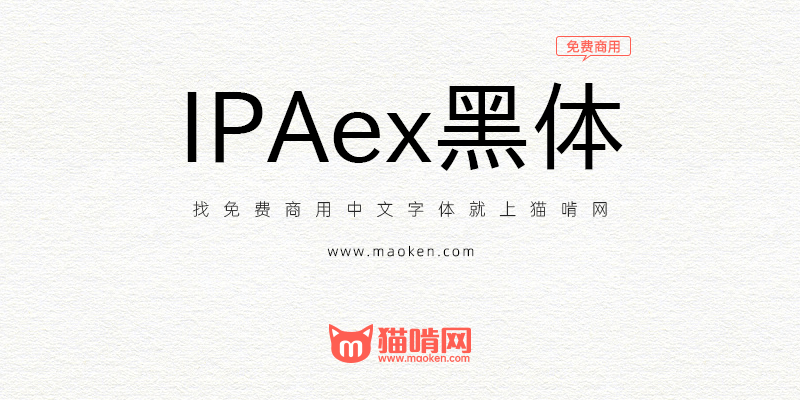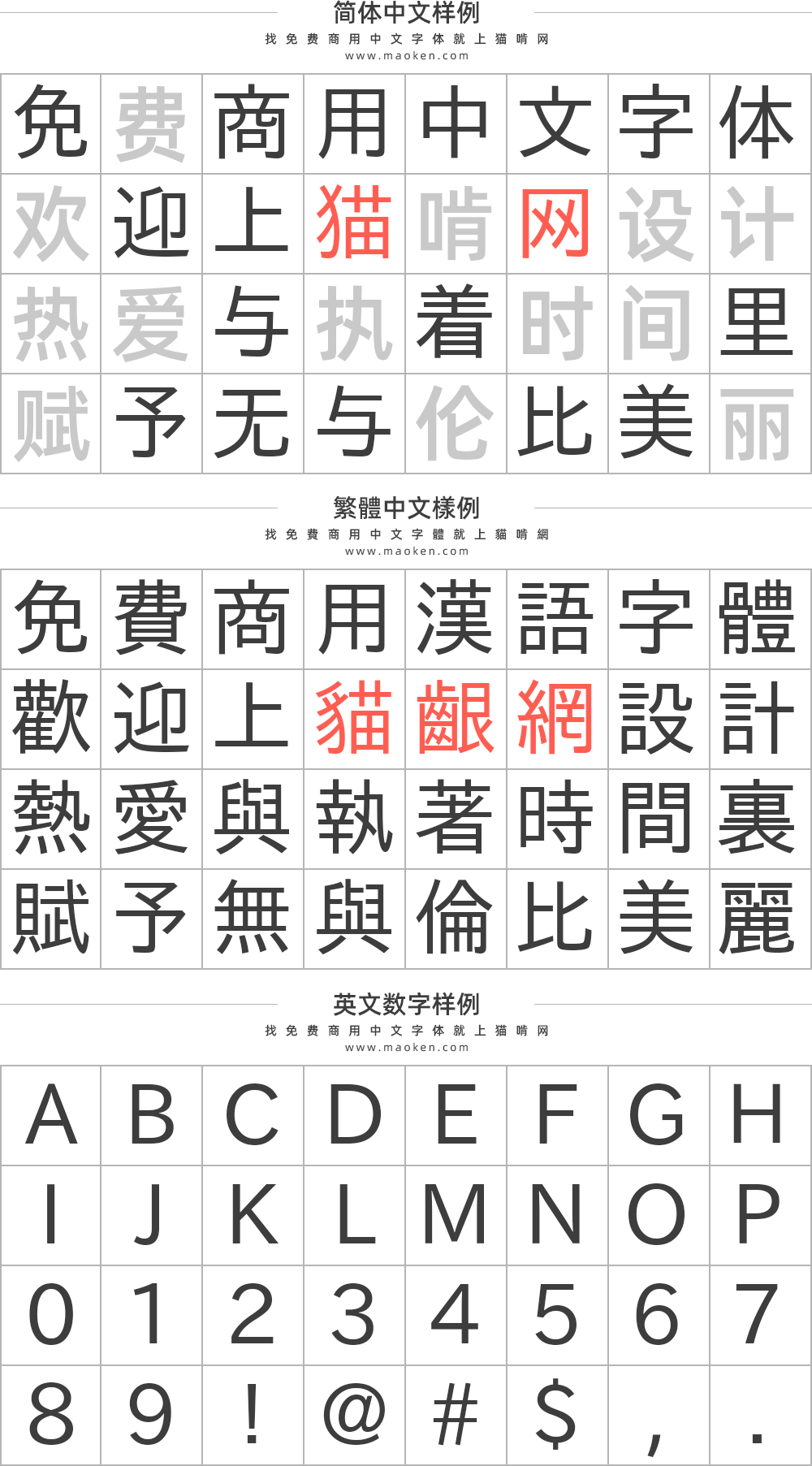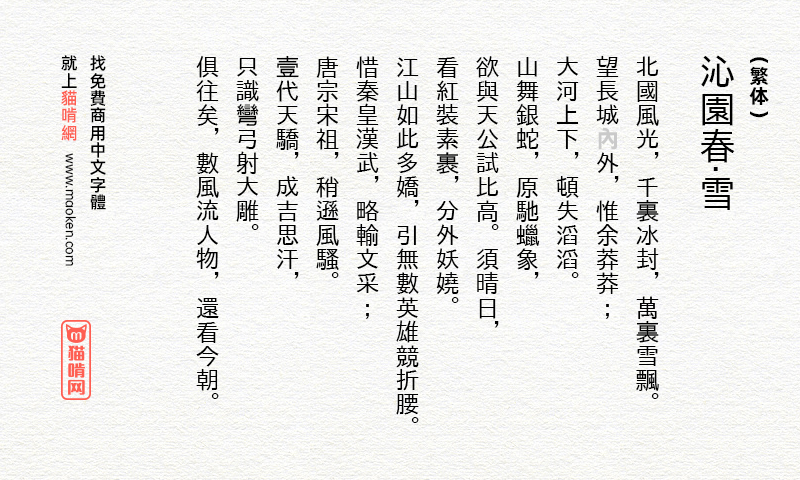
IPAex黑体:一套中规中矩的日系黑体字型
IPAex黑体是日系字体,所以简体缺字比较多。不过热心的国内设计师@落霞孤鹜为IPAex黑体这一高质量的日文字体补全简繁常用字,字体命名为霞鹜新晰黑。大家可以移步至霞鹜新晰黑进行下载简繁基本上不缺字的版本。
IPA从2003年开始提供“IPAFont*”系列,IPA拥有该系列的所有权利,并于2010年2月发布了“IPAex Mincho”和“ IPAex黑体 ”。IPA字体是日本OpenType字体,JIS X 0213:2004兼容,由日本信息技术促进机构提供。这种字体是基于哥特式(无衬线)风格,并包含比例拉丁文和固定宽度的日文字体。
本人将把这款字体补全简繁体常用字发布出来,包含 GB 2312、GB 12345,以及粉圆字库里的 CJK 统一汉字部分,部分汉字做成了旧字形。预计会在考研结束之后,元旦之前。